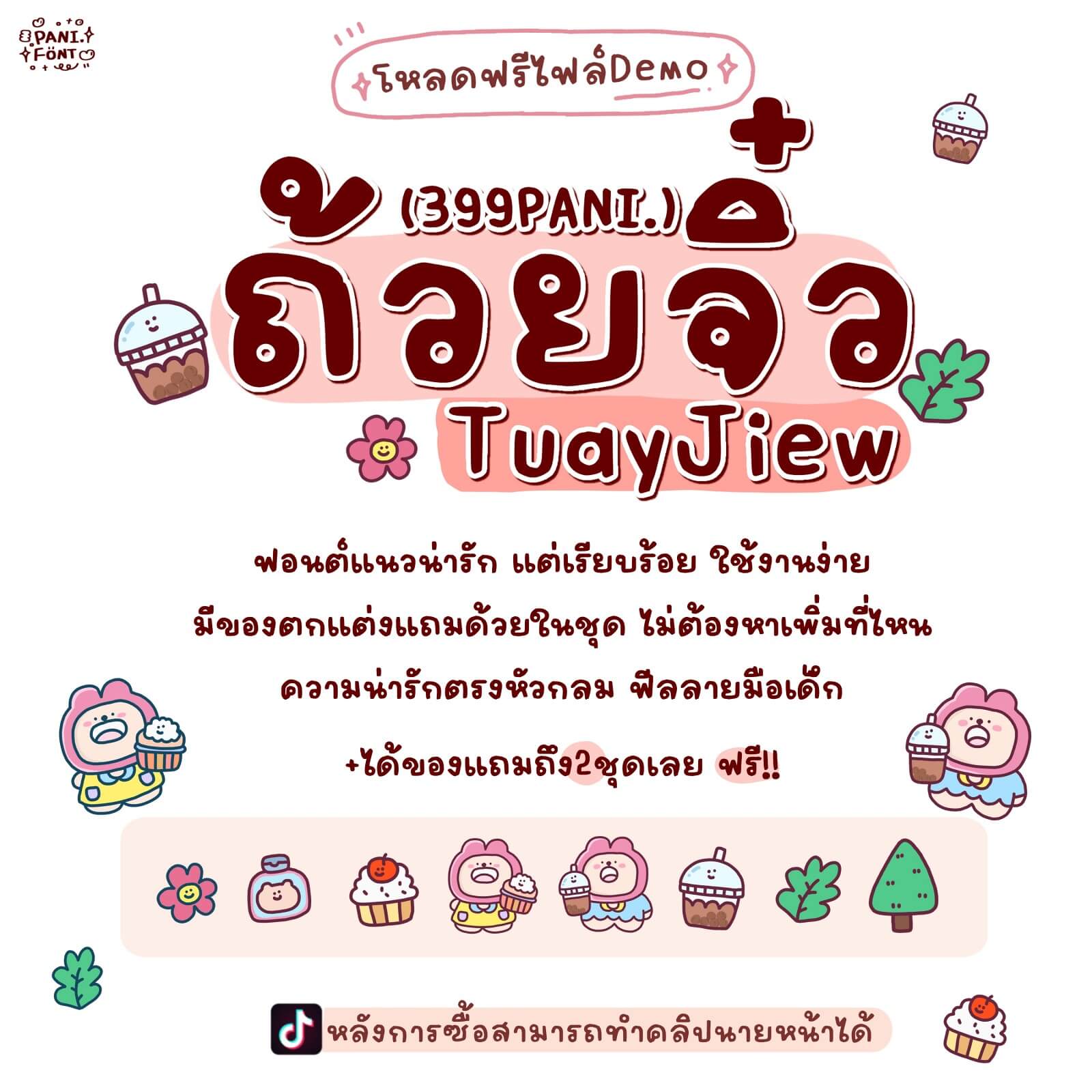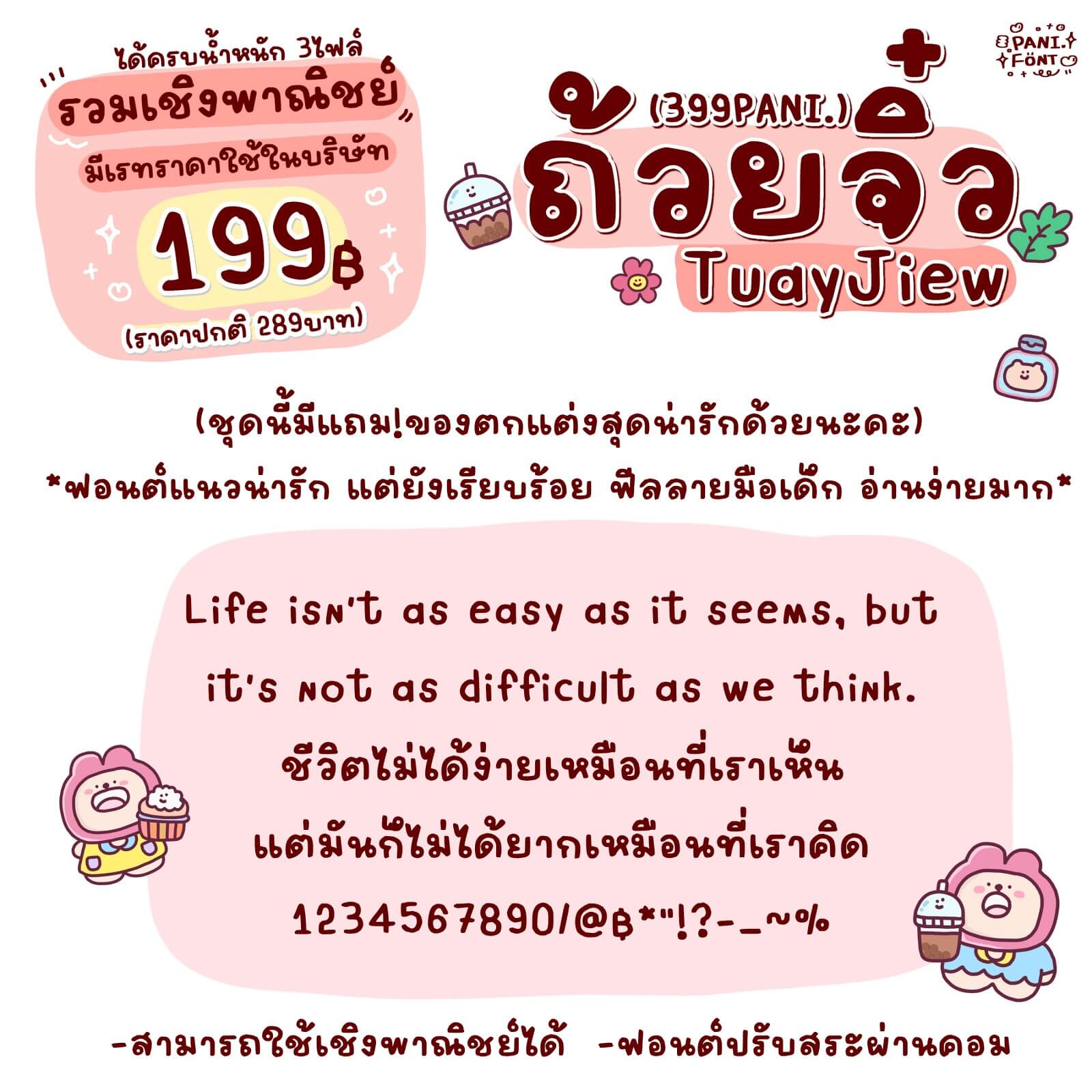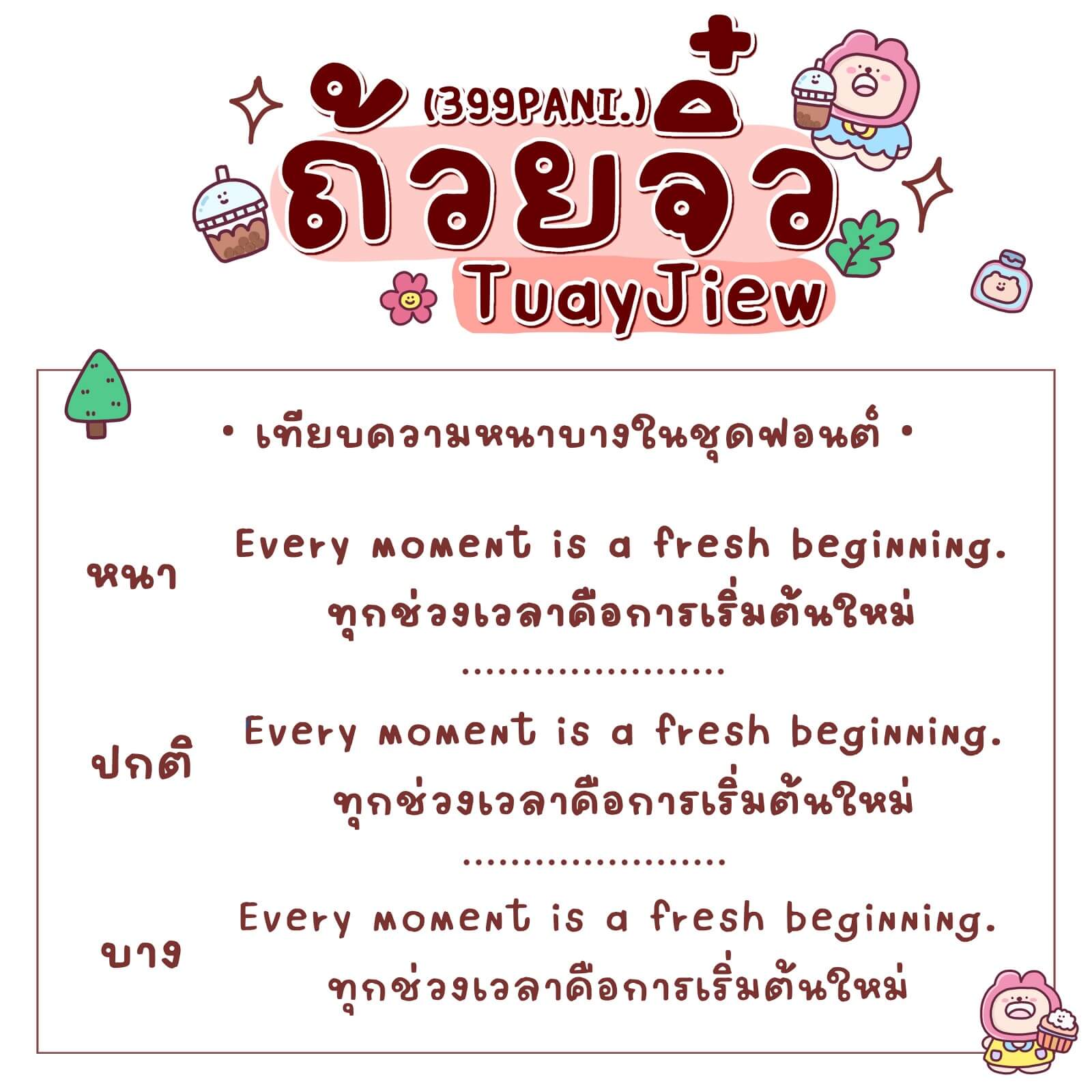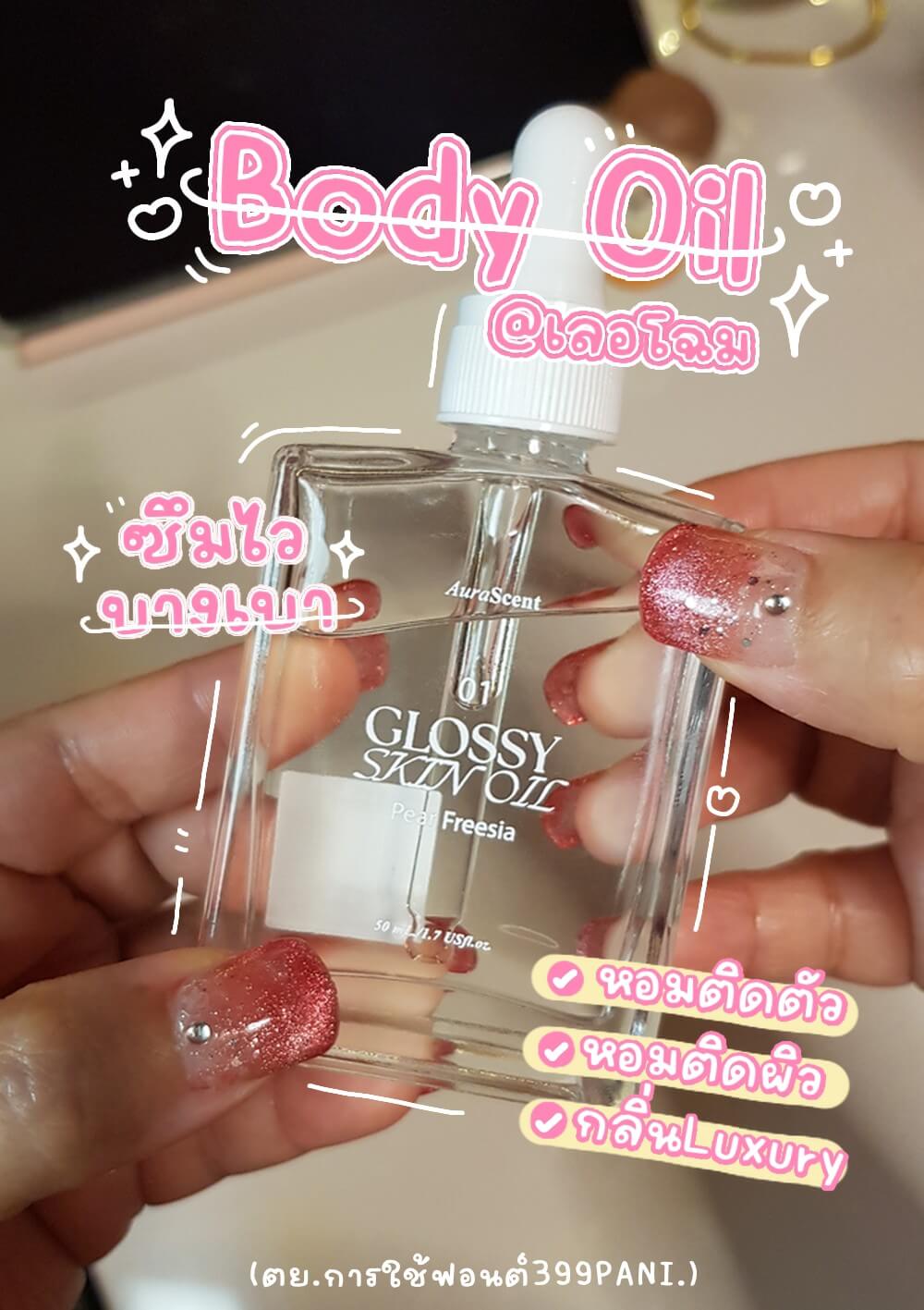
399PANI.ถ้วยจิ๋ว
ฟอนต์ 399PANI.ถ้วยจิ๋ว – ฟอนต์แนวน่ารัก แต่เรียบร้อย ใช้งานง่าย มีของตกแต่งแถมด้วยในชุด ไม่ต้องหาเพิ่มที่ไหน
ความน่ารักตรงหัวกลม ฟีลลายมือเด็ก